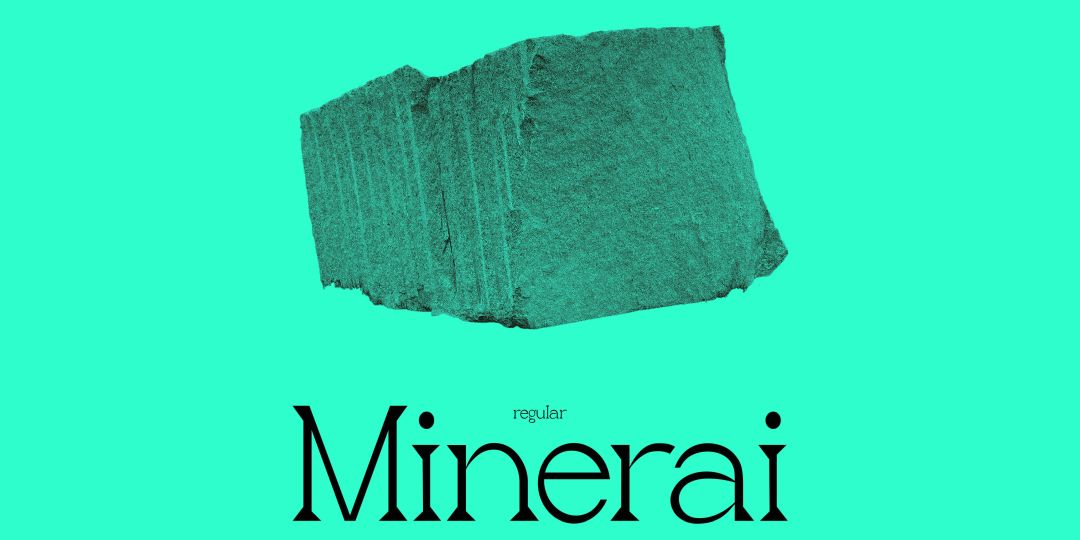
Minerai Serif
大きなセリフが特徴的なローマンディスプレイ。コントラスト弱めのややジオメトリック寄りなグリフに、大きなウェッジ型のセリフが付いた書体で、ストロークはほぼモノラインだが、ストローク同士がぶつかる所が若干テーパードになっている。作者が幼少期に故郷のポルトガルで見かけた書体が元となっているそうで、フランス語で「鉱石」の名の通り、石に刻んだような形のセリフを意識してデザインしたらしい。同じ骨格のサンセリフも別にあり。1ウェイトのみ。